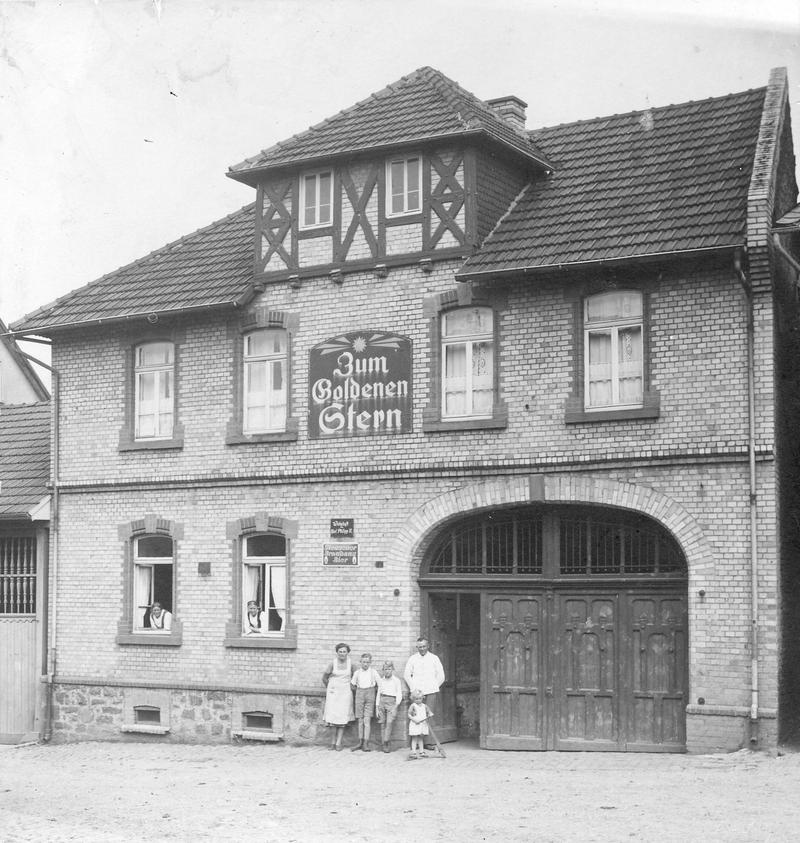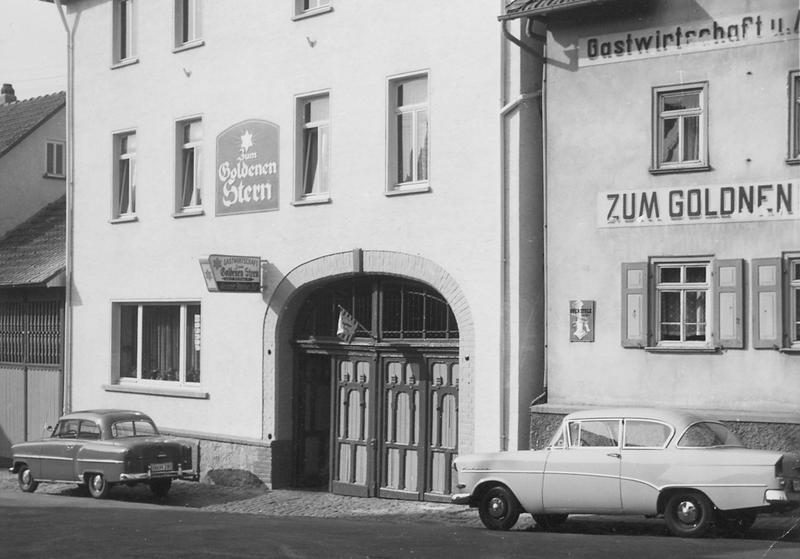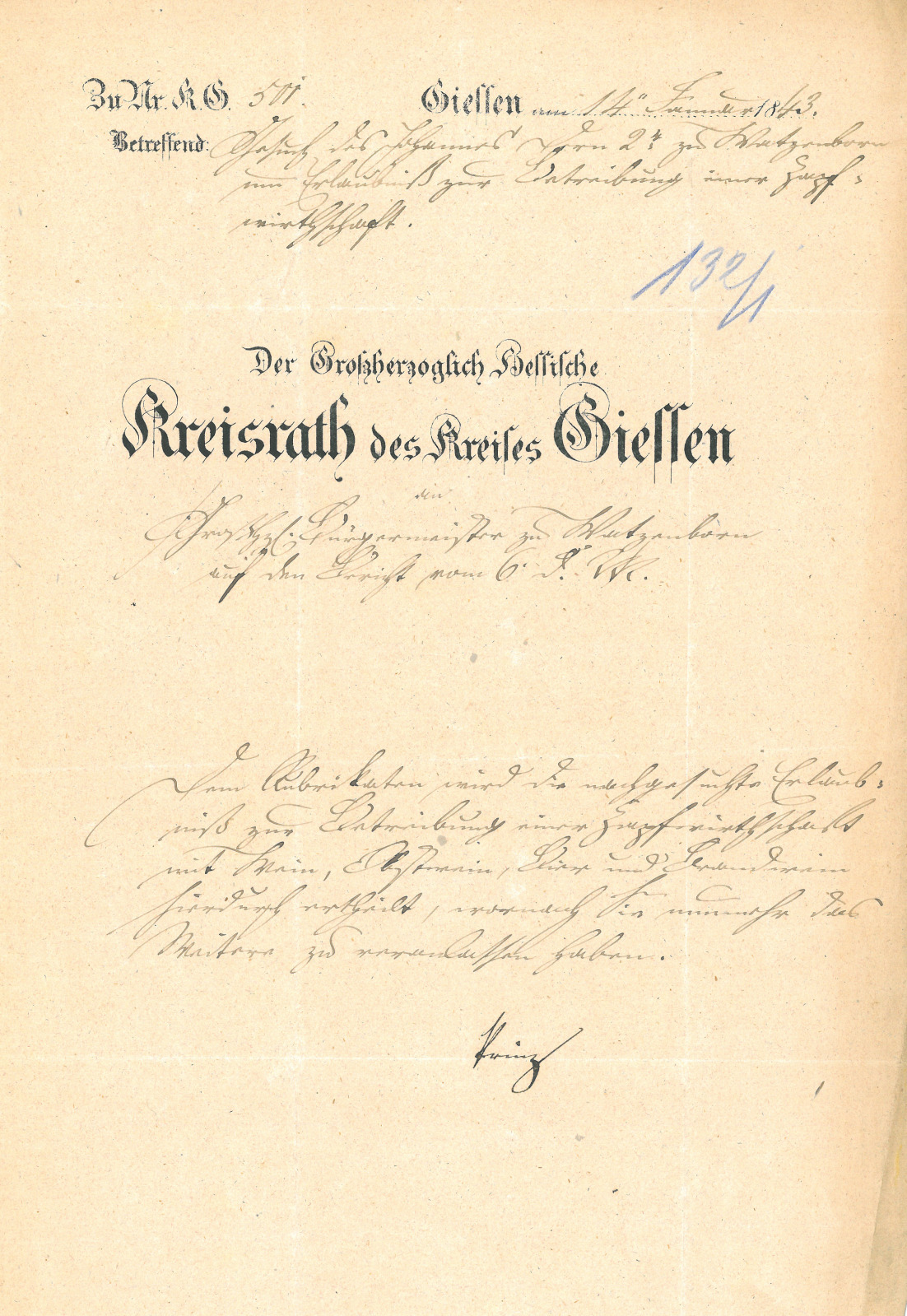
Altdeutsche Schrift gesucht
meine Eltern führen schon seit 25 Jahren ein kleines Hotel in Mittelhessen.
Es wurde bereits 1843 gebaut und ist schon immer in Familienbesitz.
Sie sind bereits die sechste Generation und die siebte (meine Schwester) steht
kurz vor der Übernahme. Wo findet man schon noch sowas heute?!
Im Herbst steht ein Umbau des Restaurants an und ich möchte,
dass ab dann endlich der gestalterische Fokus auf die Tradition und
die Geschichte des Hauses gelegt werden.
Alte Fotos groß auf Leinwand drucken lassen oder in Rahmen mit Passepartout
an die Wände hängen und vielleicht auch was mit Folie oder Profilbuchstaben
in Szene setzen. Evtl. eine große "1843" oder einen Zeitstrahl.
Leider existieren nicht mehr viele Bilder oder Antiquitäten aus der Vergangenheit.
Die fünfte Generation hatte irgendwann wohl leider mal einen Wegwerfwahn ...
Lange Rede, welche Schriften passen in diese Zeit und vermitteln Tradition und
könnten sich gut an den Wänden oder in Headlines machen?
Gibt es z.B. "typische" Fonts für Mittelhessen, die ab 1843 in Gebrauch waren?
Fette Fraktur muss nicht sein. Eine Wittenberger Fraktur? Welche Schrift kommt
der Altdeutschen nahe, die noch von den Omas geschrieben wurden?
Irgendwelche Bauernschriften, die typisch deutsch/hessisch sind?
Können auch Antiqua sein.
Ich habe auch noch zwei Fotos, mit unterschiedlichen gebrochenen Schriften.
Wer erkennt diese? Leider keine Jahreszahlen zu den Bildern vorhanden.
Habe mir auch eben "Fraktur mon Amour" bestellt. Vielleicht finde ich auch dort
Antworten oder Inspirationen.
als erstes fiel mir da die Valuta ein:
Das hört sich interessant an. Solange man versucht nicht in die historisierend kitschigen Fettnäpfchen zu treten, kann das sehr spannend werden :-D
Danke für den Tipp, Schnitzel. Die Voluta besitze ich auch, aber ich denke, dass sie für meinen Zweck zu "fein" und royal ist.
Warn mich bitte mal vor, welche Klischees du meinst, dann kann ich es gleich beachten ...
Ich habe auch noch zwei Fotos, mit unterschiedlichen gebrochenen Schriften.
Wer erkennt diese? Leider keine Jahreszahlen zu den Bildern vorhanden.
Eventuell sind auf den eigentlichen Photos mehr Anhaltspunkte zu erkennen, aber ich würde insbesondere beim ersten vermuten, dass die Schrift selbstgezeichnet, ‑geschnitten, ‑gelaubsägt oder was auch immer ist. Hierfür sprechen das seltsame r, die weggequetschte Unterlänge des Z, der Zierschwung beim m und Unsauberheiten bei S und G und der schmale untere Abschluss von l und t. Beim zweiten Beispiel sieht es so aus, als wäre das S so gestaltet, dass es sich an das G und o der Zeile darüber anpasst.
Die Schrift am Haus sieht mir auch aus, als hätte der Schildermalermeister eine gute Arbeit abgeliefert.
Ob es nun unbedingt eine Schrift aus dem Gründungsjahr des Gasthofes sein muß, weiß ich nicht. Wichtiger ist doch, daß Du eine Schrift findest, die das ausdrückt, was Du willst. (Tradition, Kontinuität, Verlässlichkeit, Grundgediegenheit ?)
Und wenn Du keine passende Schreibschrift findest, kannst du es immernoch wie 1843 machen. Nämlich selbst schreiben. :-)
Ist jemand in der Lage, dieses Dokument für mich komplett "übersetzen" zu können?
Ich bin leider nicht fähig alles lesen zu können ...
Das ist die Erlaubnis zum Betrieb einer Zapfwirtschaft. Für eine vollständige Transskribtion fehlt mir im Moment die Zeit, auch wäre ein höher aufgelöster Scan möglicherweise hilfreich.